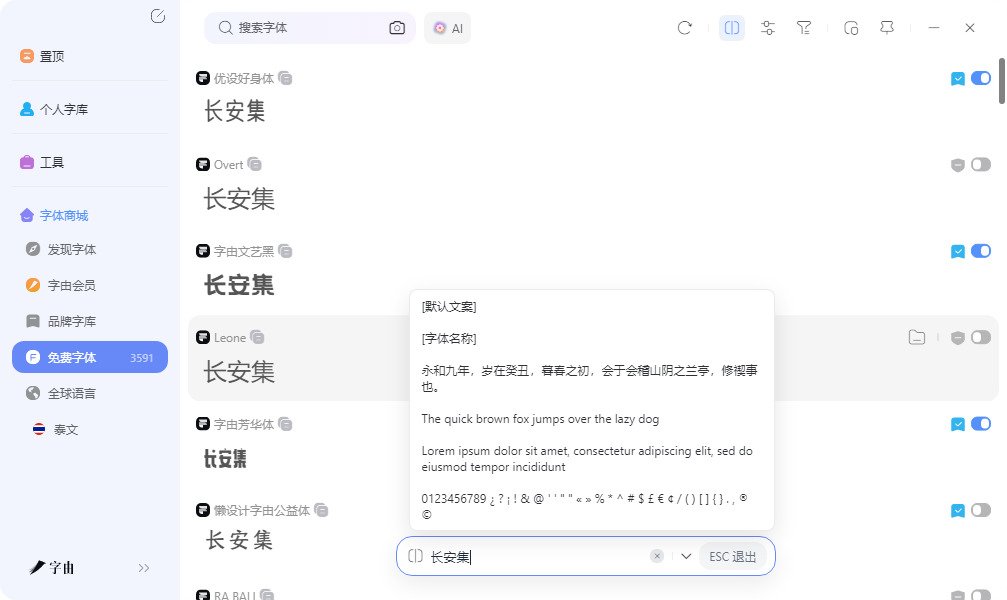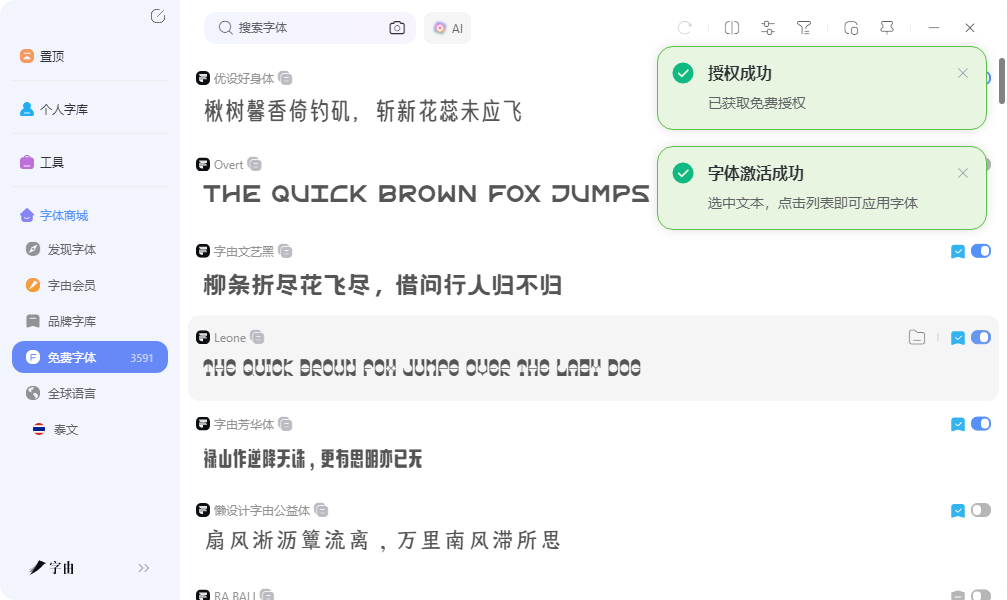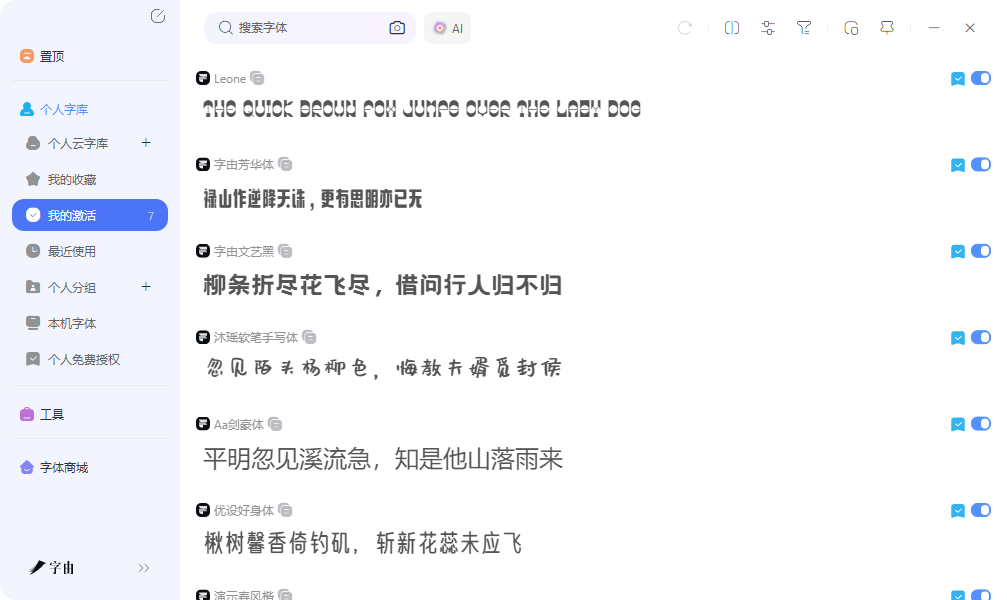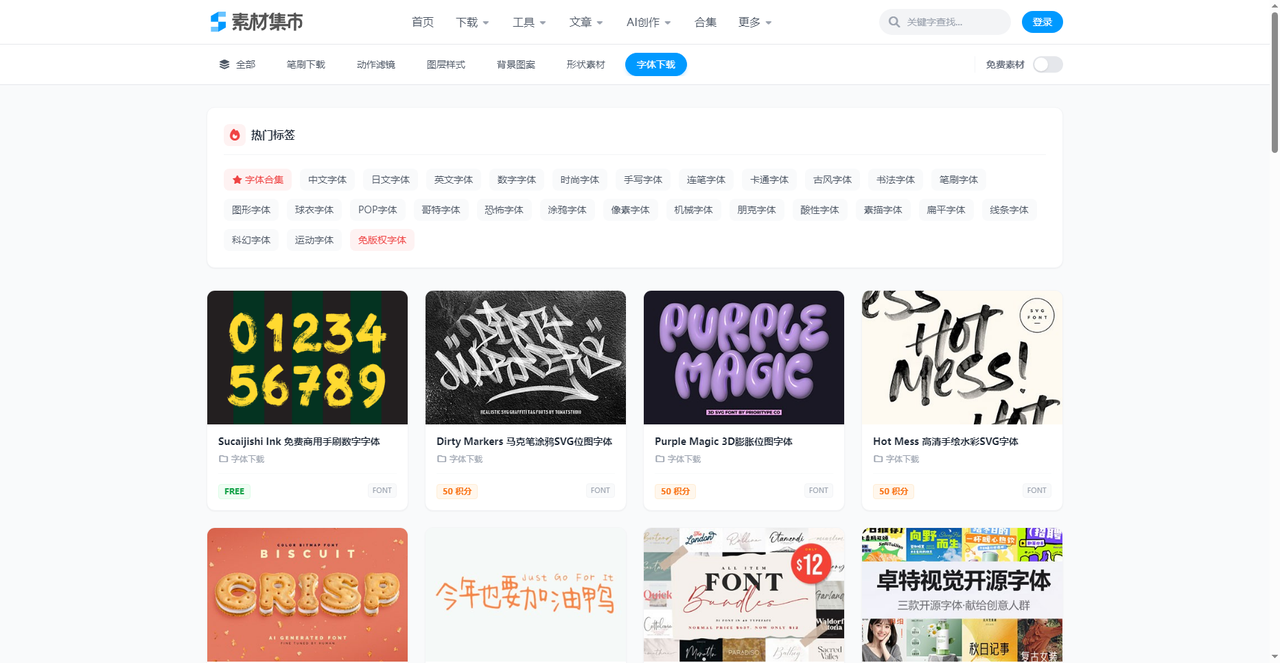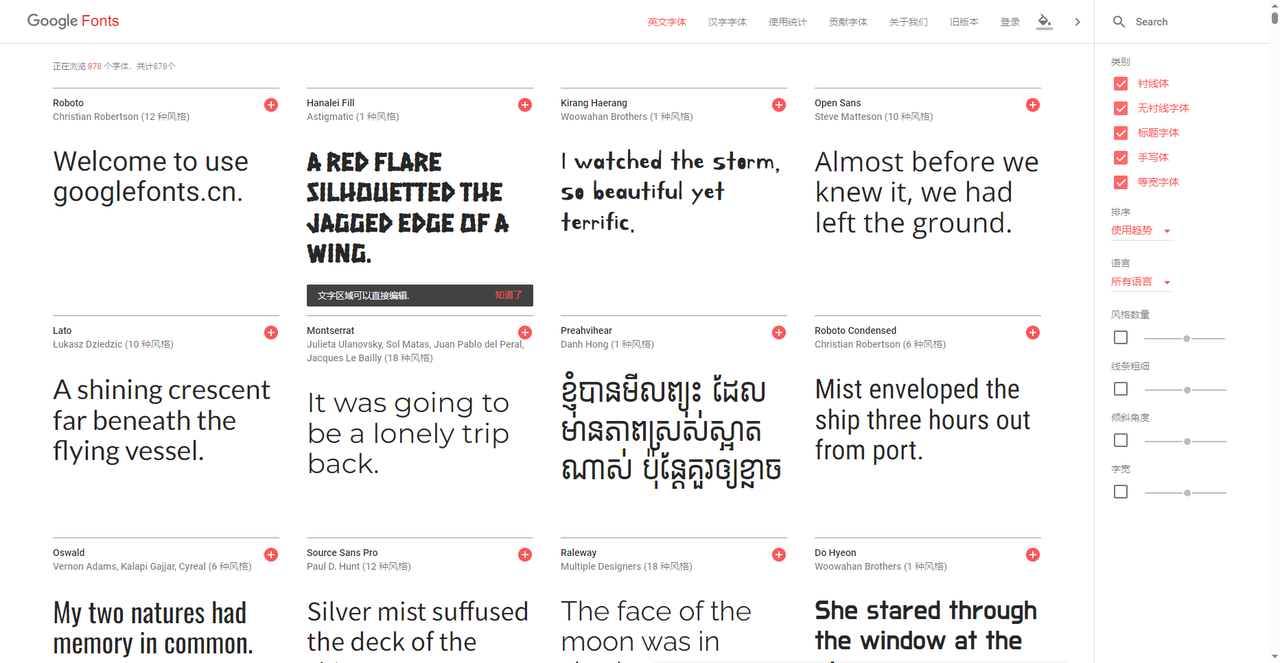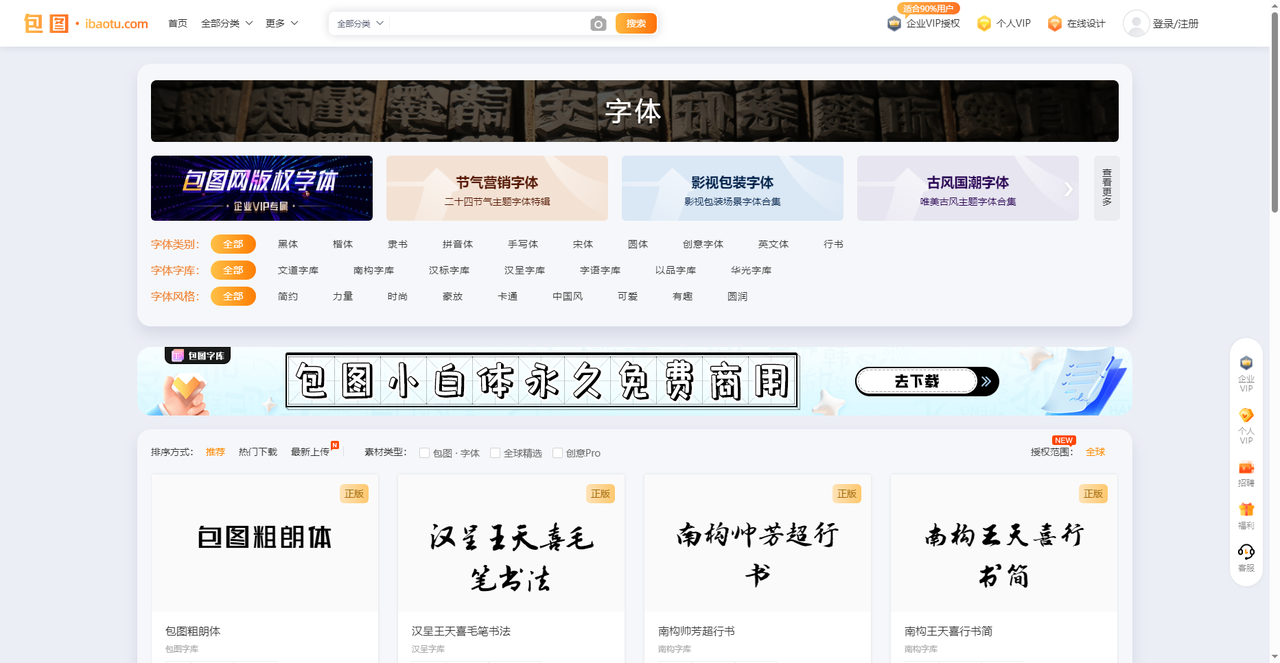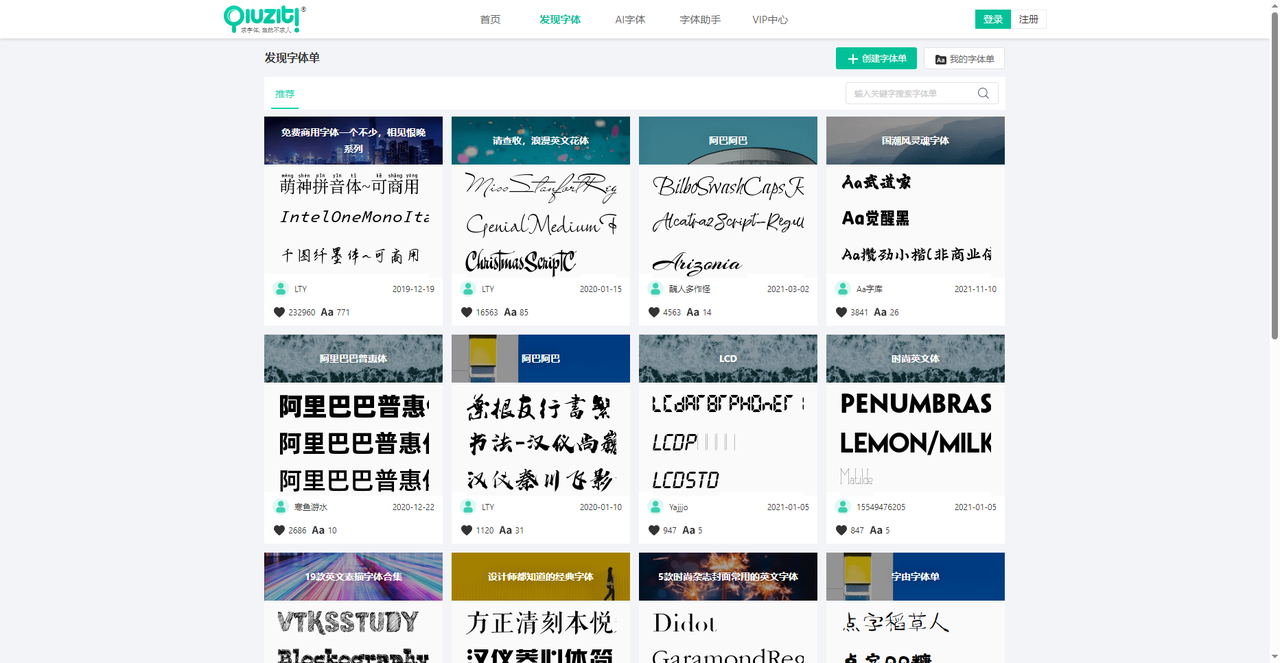
下载字体不用愁,认准这几个靠谱资源站
做设计少不了装字体,但网上一搜“字体下载”,出来的网站十个有八个不靠谱。有的满屏广告,点下载下来的是exe;有的字体装完才发现缺字符;更麻烦的是,很多字体写着“免费”,实际只能用个人用途。今天不推荐那种来路不明的“字体大全”,只说几个真正靠谱的下载渠道。有用字体助手字由这样的云端激活工具,也有开源字库和老牌素材站。总有一个适合你,需要的话记得收藏本篇文章。
先聊字由。传统下载字体,你得先在网上找到下载链接(这一步最容易踩坑),字由则是帮你省了很多繁琐的步骤。打开字由客户端,上面直接有上万款字体,按风格、语言、类型分好了类。左侧筛选栏里,你可以按“字体类型”选黑体、宋体、圆体、手写体、书法体、创意字体等;也可以按“字体语言”选简体中文、繁体中文、英文、日文、韩文等;还可以按“授权类型”选免费商用、会员商用。每款字体都有预览图,输入你自己的文案——比如你的品牌名“长安集”或者一句slogan“值得等待”——页面会实时显示这款字体写出来的样子。不用下载,不用安装,就知道合不合适。
找到喜欢的字体后,点一下右侧的“激活”按钮。按钮从灰色变成绿色,这款字体就“激活”了。然后你打开PS、AI、Word,在字体下拉菜单里就能直接看到它,不需要重启软件。从“看到”到“用上”,中间没有下载、解压、复制、重启这一堆步骤。
字由还有一个“个人云字库”功能。你在公司电脑上激活过的字体,可以收藏到云端。晚上回家打开笔记本,登录同一个字由账号,之前激活的字体一键同步,不用重新找、重新激活。字由客户端支持Windows和macOS,安装包只有几十MB,注册后就可以使用。如果你是一个需要在多台设备之间切换工作的设计师,这个功能省下的时间不是一点点。
字由的字库覆盖了黑体、宋体、圆体、手写、书法、卡通、创意等几乎所有风格。比如你需要一款适合做标题的粗体字,可以在筛选栏里勾选“英文+展示体+粗重”,系统会把所有符合条件的字体列出来;你需要一款手写感的中文字体,勾选“简体中文+手写体”,几十款钢笔手写、毛笔手写、儿童手写风格的字体出现在眼前。每款字体都可以实时预览,输入你的文案直接看效果。
2、素材集市
第二个网站是素材集市。它是一个设计素材聚合平台,字体是其中一个大类。分类非常细致:中文字体、日文字体、英文字体、数字字体、时尚字体、等。每款字体都有预览图,部分标注了“免版权”“免费商用”。例如截图中的“SucaijishiInk免费商用手刷数字字体”“DirtyMarkers马克笔涂鸦SVG位图字体”“PurpleMagic3D膨胀位图字体”“HotMess高清手绘水彩SVG字体”等。下载需要积分或免费获取。适合找创意字体、风格化字体的设计师。
3、Google Fonts
第三个网站是Google Fonts。全球最大的开源字体库,收录了878款字体,全部免费,全部开源。Roboto、Open Sans、Lato、Montserrat、Oswald等经典字体都在这里。每款字体都标注了设计师名字、风格数量、支持的语言。Google Fonts的优势:字体质量高、授权清晰(SIL OFL或Apache协议),可以放心用于任何项目,包括商业用途。下载方式简单:点击字体进入详情页,选择字重和样式,下载TTF或使用网页嵌入代码。缺点是中文字体极少,只有Noto Sans SC等几款,主要是英文字体。如果你需要英文字体,Google Fonts是首选。
4、包图网
第四个网站是包图网。它是一个企业级设计素材平台,字体板块提供了大量商用授权字体。分类明确:黑体、楷体、隶书、拼音体、手写体、宋体、圆体、创意字体、英文体、行书等。还有按场景分类:节气营销字体、影视包装字体、古风国潮字体等。包图网的字体大部分需要VIP会员或企业授权才能下载使用。截图中的“包图粗朗体”“汉呈王天喜毛笔书法”“南构帅芳超行书”等都是正版字体,适合需要采购授权进行商业项目的公司或设计师。如果预算有限,也有永久免费商用字体,比如“包图小白体”
5、字体单资源站
第五个工具是一个字体列表平台。上面有用户整理的各类字体单,比如“免费商用字”“浪漫英文花体”“国潮风灵魂字体”“萌神拼音体~可商用”等。每个字体单下面列出了具体字体名称和来源,方便批量下载同类型字体。例如“Aa武道家”“千图纤墨体”“阿里巴巴普惠体”等都已经标注了是否可以商用。对于需要快速找到同类风格字体的设计师来说,这种整理好的清单很省时间。
五个字体下载渠道,最方便的我觉得是字由。字由适合不想折腾安装、需要跨设备同步字体的设计师,点激活就能用;素材集市提供大量创意风格字体,适合做海报标题和装饰文字;Google Fonts是英文字体的最佳来源,开源免费且质量高;包图网适合企业采购正版授权字体;字体单资源站则提供整理好的字体清单,方便批量下载同类风格。根据你的项目需求,选一个最顺手的就行。下载前花几秒钟确认授权类型,养成习惯,可以避免很多麻烦。